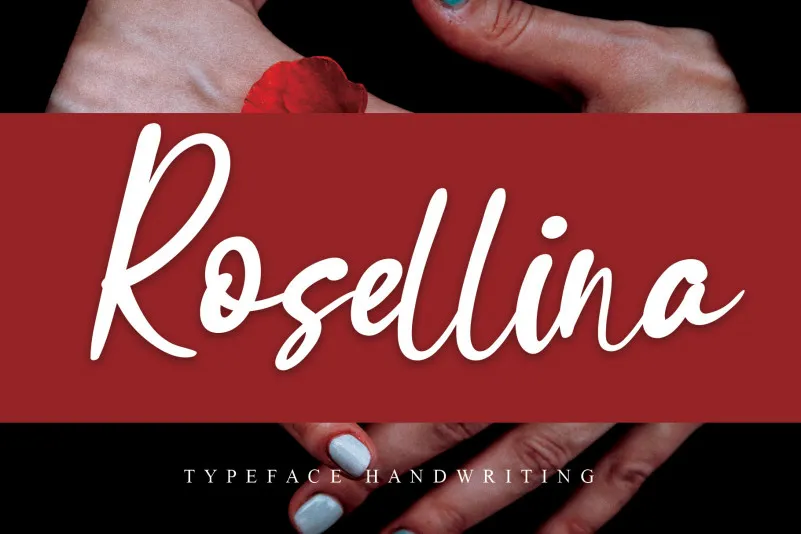
Rosellina Script Font
A Rosellina Script Font é uma elegante fonte a mão escrita que se destaca pela sua sensibilidade e naturalidade. Inspirada nas belas letras cursivas de alguém escrevendo com amor, essa fonte perfeita para projetos pessoais e artesanatos. Seu estilo único e eterno é ideal para criar designs memoráveis ​​que encantam os olhos. O que mais poderíamos querer em uma fonte a mão? A Rosellina Script Font não se limita à elegância, ela transcende com sua beleza singular e duradoura, tornando-a perfeita para qualquer projeto que você precise executar. Sempre é encantador descobrir novas maneiras de expressar-se através da escrita digital — a Rosellina Script Font oferece uma paleta infinita de possibilidades criativas ao seu alcance. Experimente e veja por si mesmo como essa font se encaixa perfeitamente em seus projetos pessoais ou comerciais.